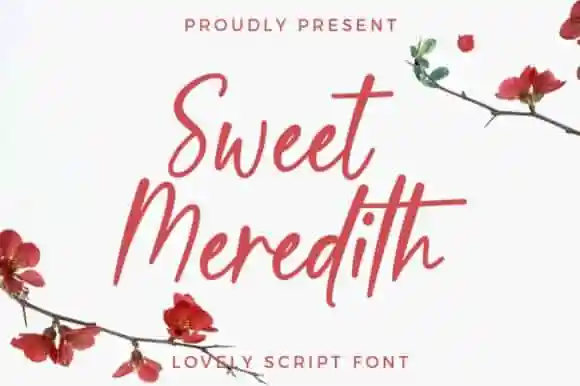
Sweet Meredith Script Font – Fonte Grátis
Sweet Meredith Script Font
A Sweet Meredith Script Font é uma delícia para qualquer designer que busca uma mistura perfeita entre modernidade e elegância. Inspirada nos urbanos, essa fonte mantém sua sofisticação com linhas afiadas e atraentes, criando designs contemporâneos, trendy e requintados. Com origem no Typesthetic Studio, esta tipografia tem um brilho único que deriva de uma calligrafia à mão com fluxos elaborados e refinados. A Sweet Meredith é perfeitamente adequada para uso em logos, decoração nupcial, cartões, designs de presentes, fotografia, marca d’água e embalagens de produtos. Ela também oferece uma incrível variedade, incluindo ligaturas, conjuntos completos de letras maiúsculas e minúsculas, símbolos multilíngues, números e pontuação. Essa fonte não apenas é versátil, mas também tornará seus projetos mais atraentes e elegantes. Com o Sweet Meredith Script Font nas suas habilidades gráficas, você terá a liberdade de expressar sua criatividade enquanto mantém um padrão de qualidade impecável. Não hesite em explorar seu potencial inexplorado. Seja você que está criando logotipos para uma marca jovem e moderna, ou produzindo cartões de decoração nupcial, essa fonte oferecerá o toque perfeito.